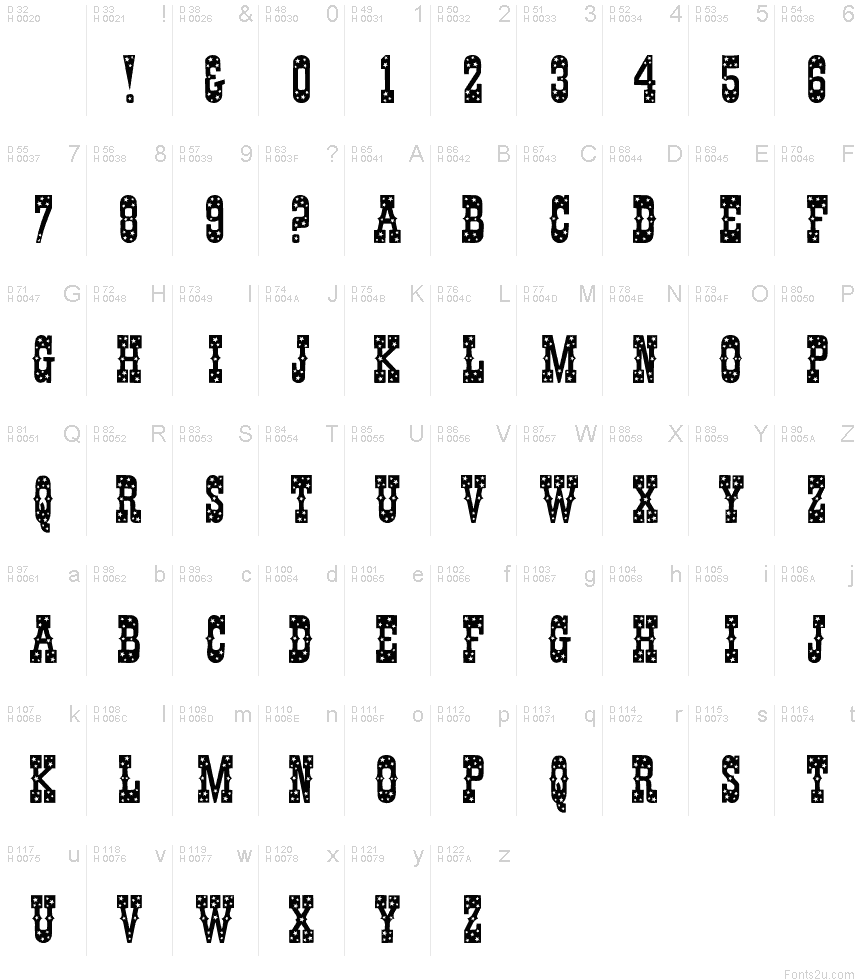
Pentagon di House of Lime è un font display gratuito in stile western, con il fascino grintoso dei manifesti di una volta. Le lettere sono grandi, nette e teatrali, con forme massicce attraversate da ritagli di stelle che donano all'alfabeto un'atmosfera da cielo notturno e da insegna da rodeo.
Si adatta naturalmente a poster, volantini per eventi, inviti a feste, copertine di album, titoli e brevi intestazioni dove questa texture stellata può parlare da sola. Essendo un font gratuito, è perfetto anche per loghi a tema, branding in stile distintivo e grafiche per scuole o comunità che cercano una voce western con un tocco di spettacolo giocoso.